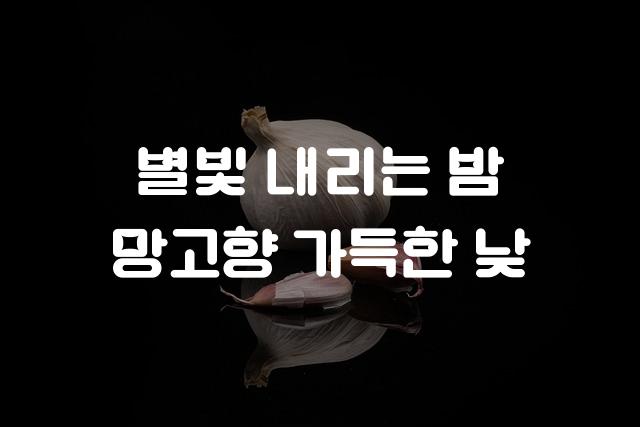
망고보드 또박체는 장식체와 둥근 고딕을 혼합한 독특한 형태로, 동글동글하고 가로로 긴 문자가 특징입니다. 이 폰트는 아늑하고 친근한 느낌을 주어 읽는 이로 하여금 편안함을 제공합니다.
망고보드 또박체은(는)
부드러움, 복실복실, 별모양/패턴, 기본 고딕, 자연감성, 감성적인, 장식 스타일, 두꺼운 스타일, 둥근 스타일 계열의 생김새를 가지고 있으며
프레젠테이션, 출판물 제목, 보고서/문서 등에서 자주 활용되며, 효과적인 메시지 전달에 적합합니다.
이 폰트는 교육, 출판/미디어, 금융/비즈니스 분야에 잘 어울리며,
단순한, 편안한, 명확한 느낌을 담고 있는 것이 특징입니다.
이 폰트와 유사한 폰트로는 나눔고딕, 배민 주아체, 휴먼모음T 등이 있어요. 함께 비교해 보시면 좋습니다!